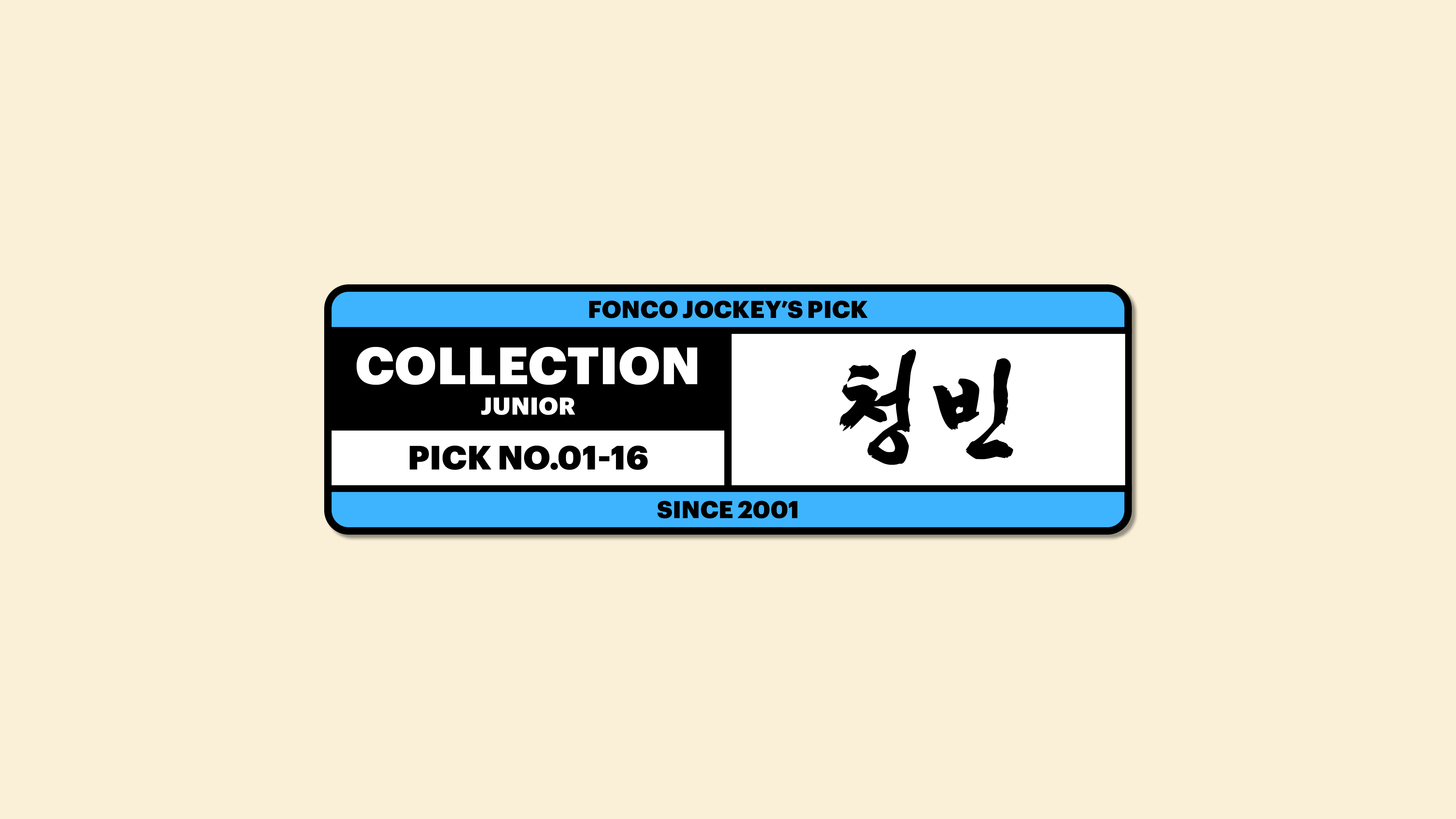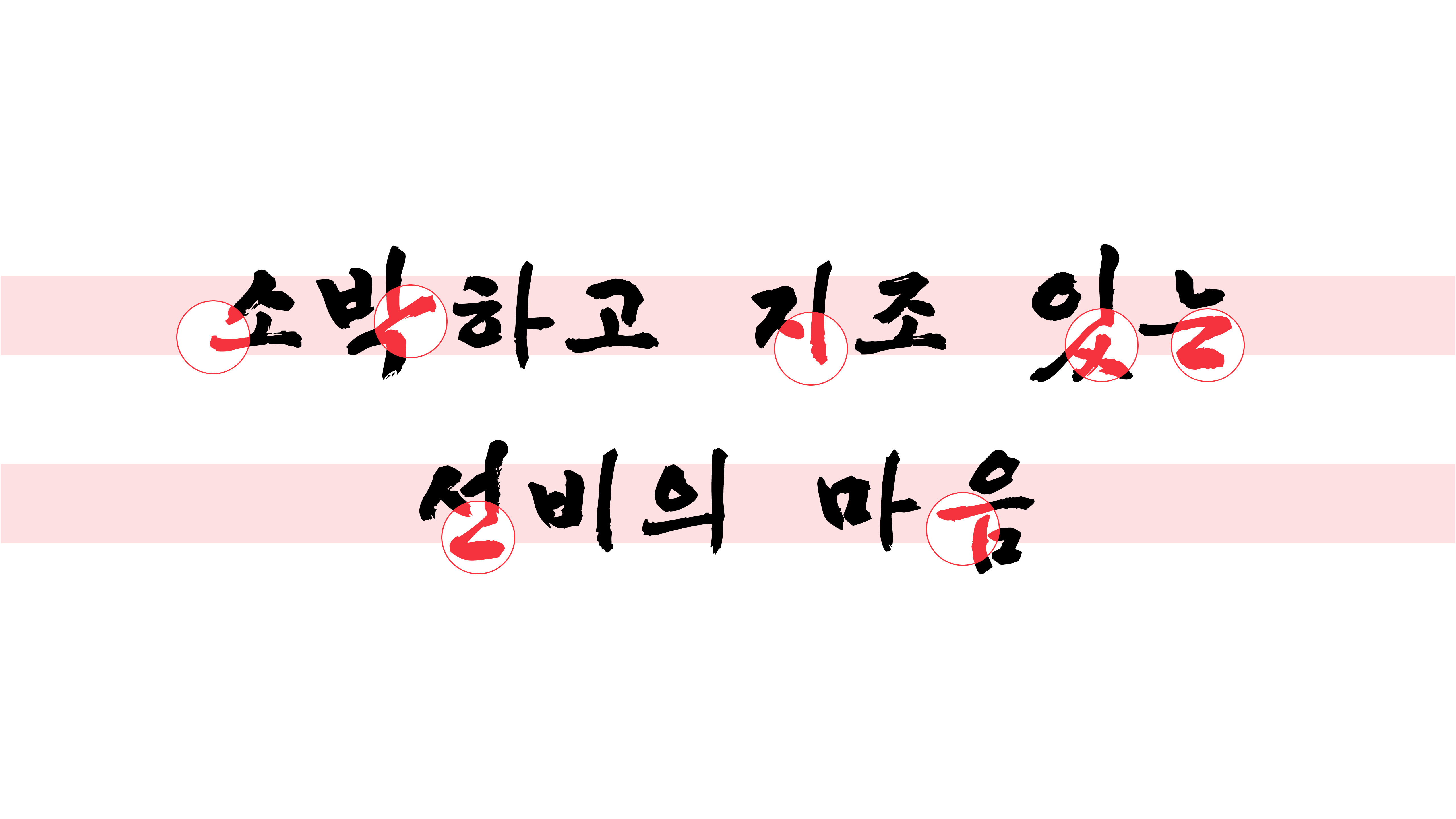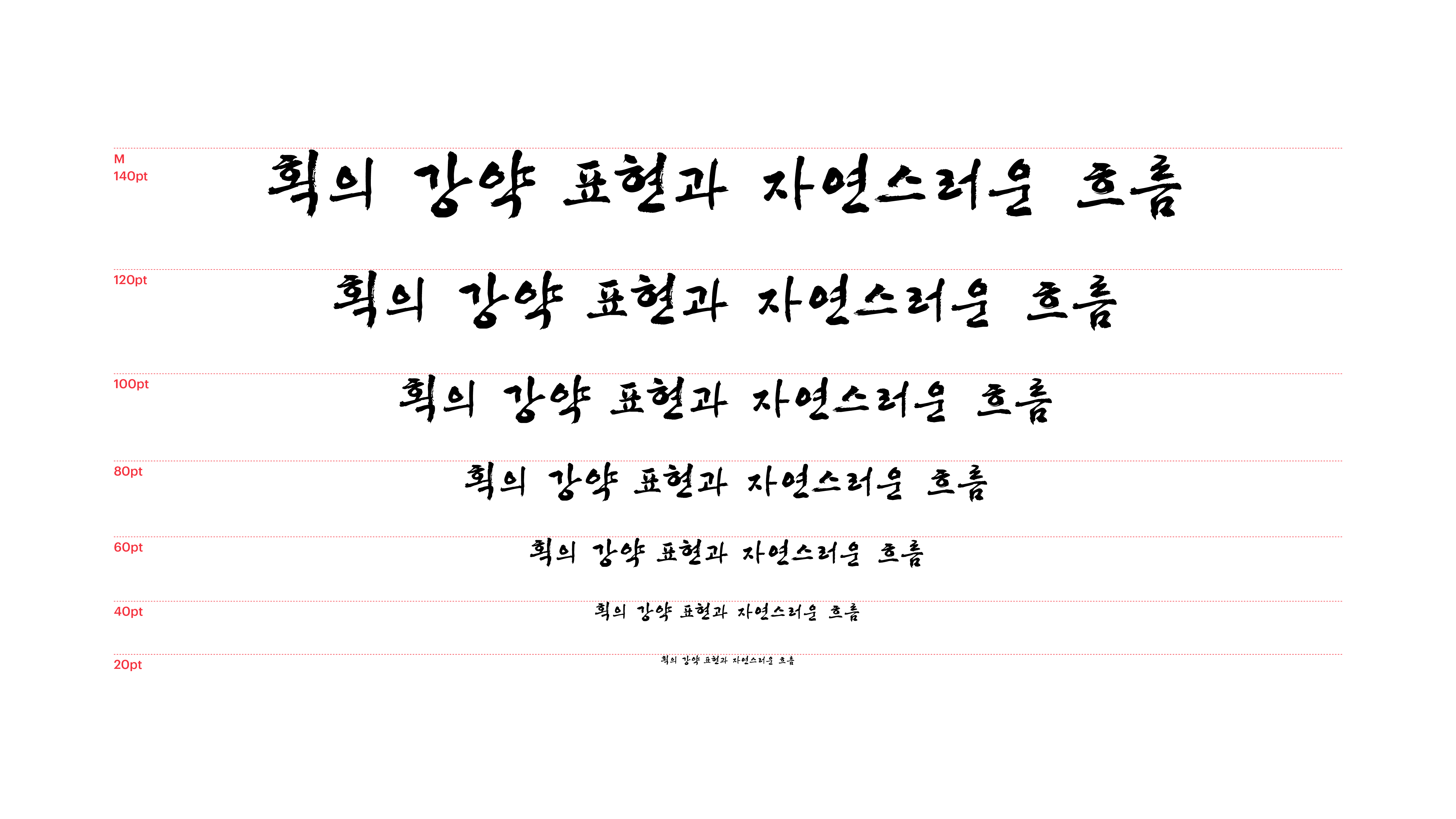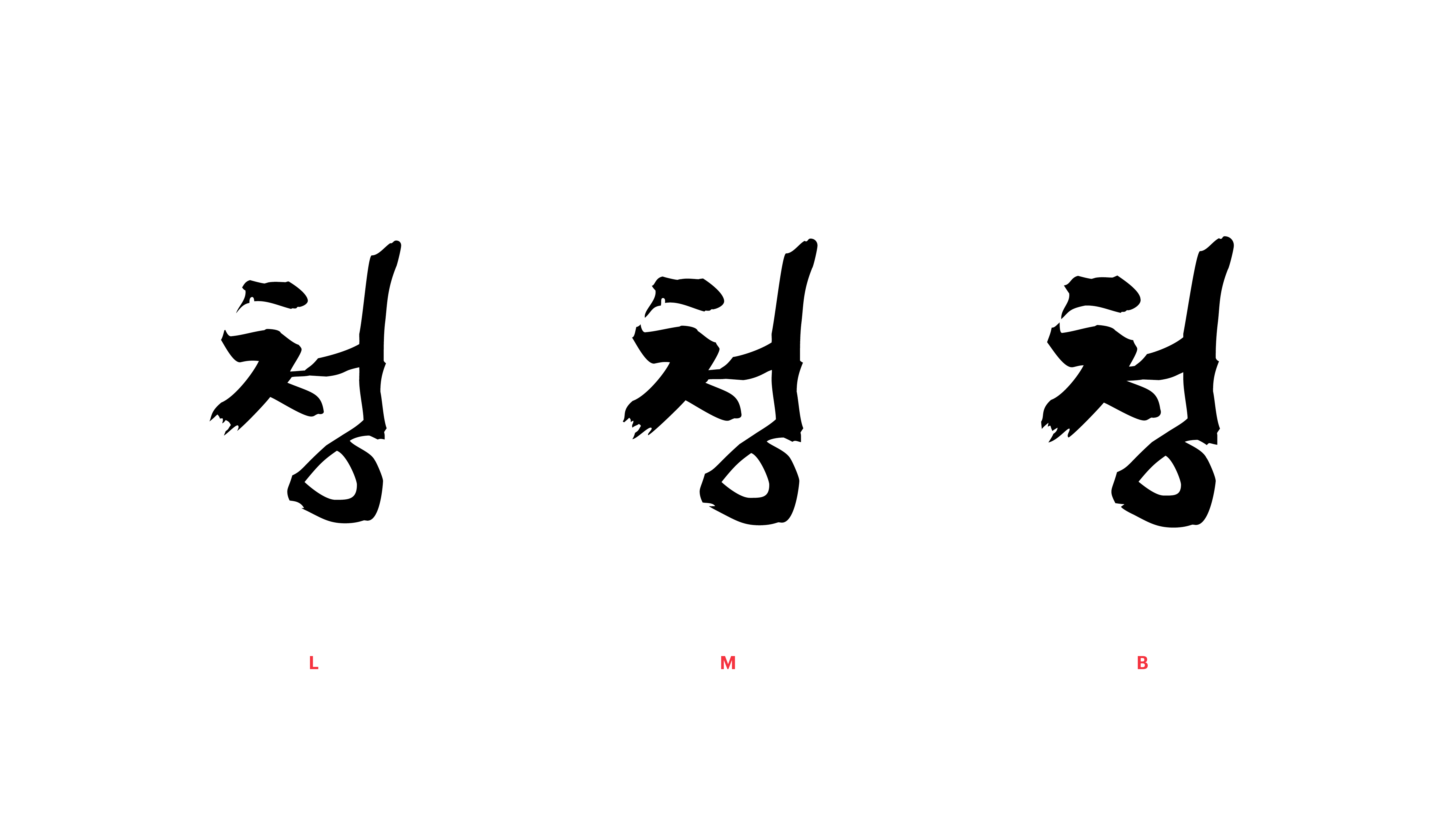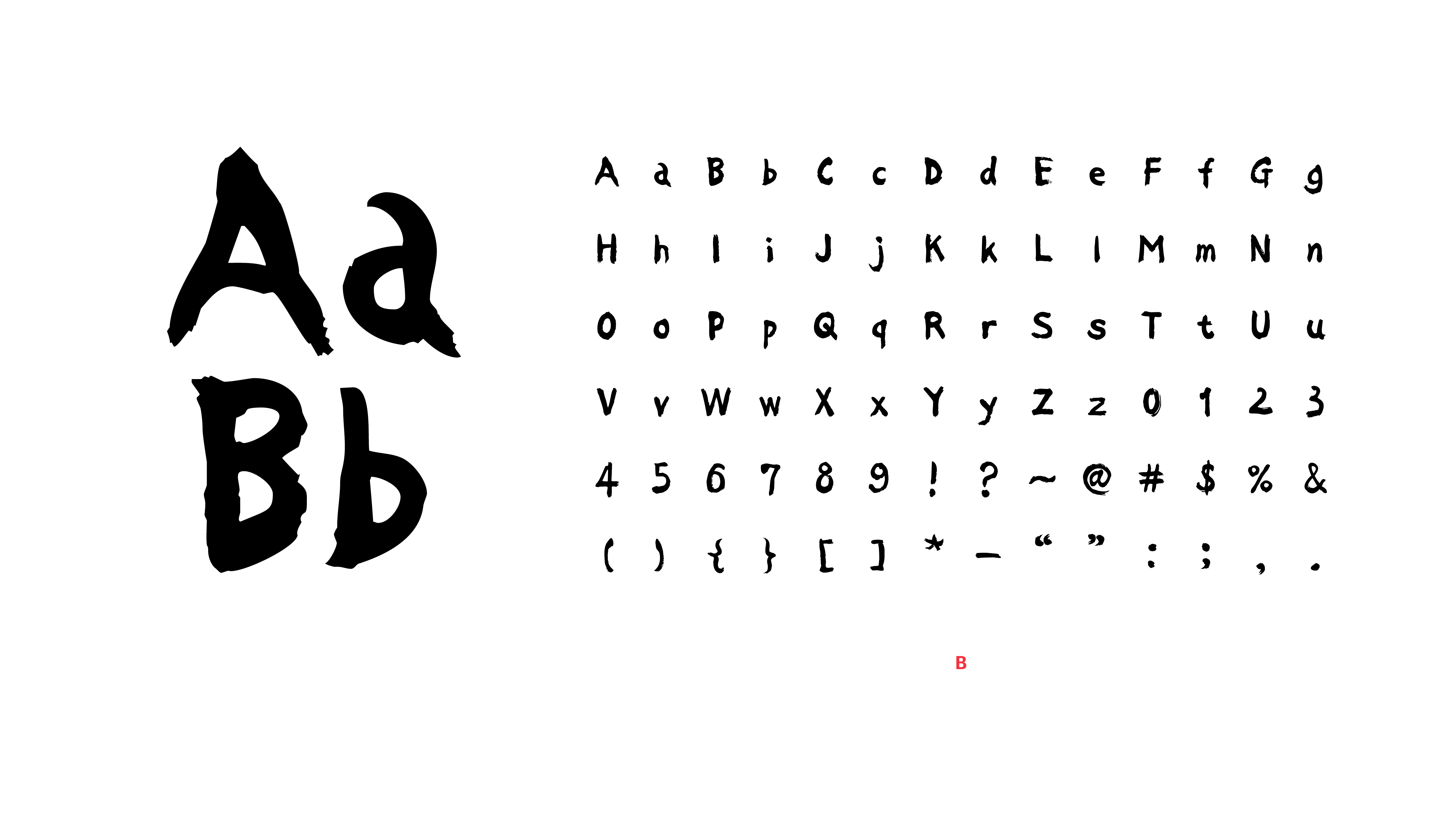
[손글씨]
청빈
Yoon 청빈
성품이 청빈하다는 것은 인품이 맑고 재물에 대한 욕심이 없다는 뜻입니다. 청빈체에는 이처럼 소박하고 지조 있는 선비의 마음이 담겨 있지요. 획의 강약이 살아있으면서도 조곤조곤 말을 하듯 자연스럽게 흐르는 이 폰트로는 어떤 말을 적어도 신뢰도가 마구마구 상승할 것 같아요.